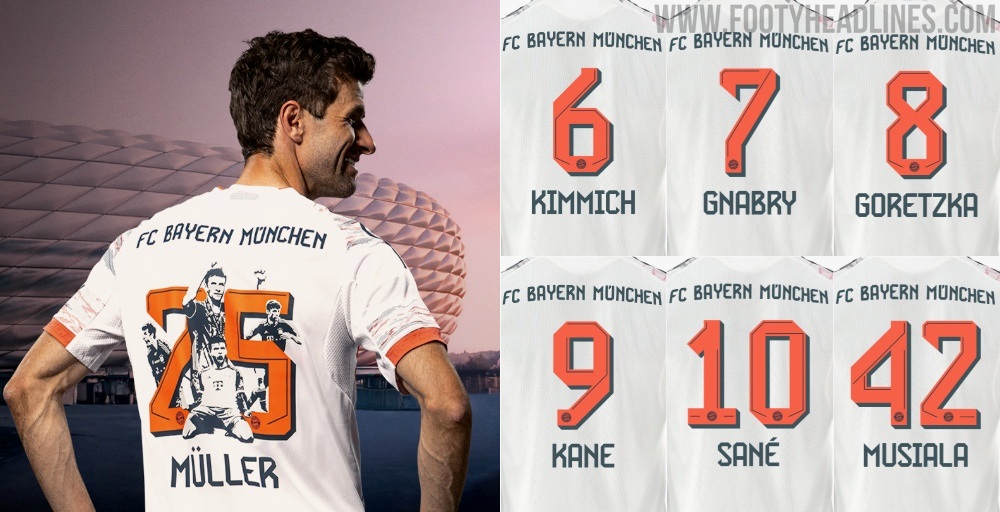
Rilasciato il nuovo font della maglia del Bayern München 25-26
- Nuovo Font Maglia Bayern Monaco 25-26:: Il Bayern Monaco ha rilasciato un nuovo font per la maglia della stagione 2025-26, con dettagli 3D.
- Struttura del Font:: La struttura di base del font rimane coerente con la stagione 2024-25, ma introduce dettagli per un effetto tridimensionale.
- Edizione Speciale Muller e Costi:: È stata lanciata un'edizione speciale del numero 25 in omaggio a Muller, portando il costo totale del kit a 170 euro.
Il Bayern Monaco ha rilasciato un nuovo font per la maglia della stagione 2025-26, che rappresenta un sottile aggiornamento rispetto alla stagione 2024-25.
Maglia Bayern München 25-26 Font
Il nuovo font della maglia del Bayern Monaco 25-26 si basa sulle fondamenta gettate dal carattere della stagione 2024-25. Mentre la struttura di base rimane coerente, la versione 25-26 introduce ulteriori dettagli per creare un effetto visivo tridimensionale (3D).
Questo conferisce ai numeri e alle lettere maggiore profondità e carattere senza compromettere la leggibilità o la coesione estetica con la maglia.
Da lontano, il carattere mantiene un aspetto pulito e moderno. Da vicino, le ombreggiature e i bordi angolati apportano un miglioramento visivo notevole rispetto all'aspetto più piatto del font della scorsa stagione.
Oltre al carattere normale, il Bayern ha lanciato anche un'edizione del numero 25 con un design che rende omaggio a Muller.